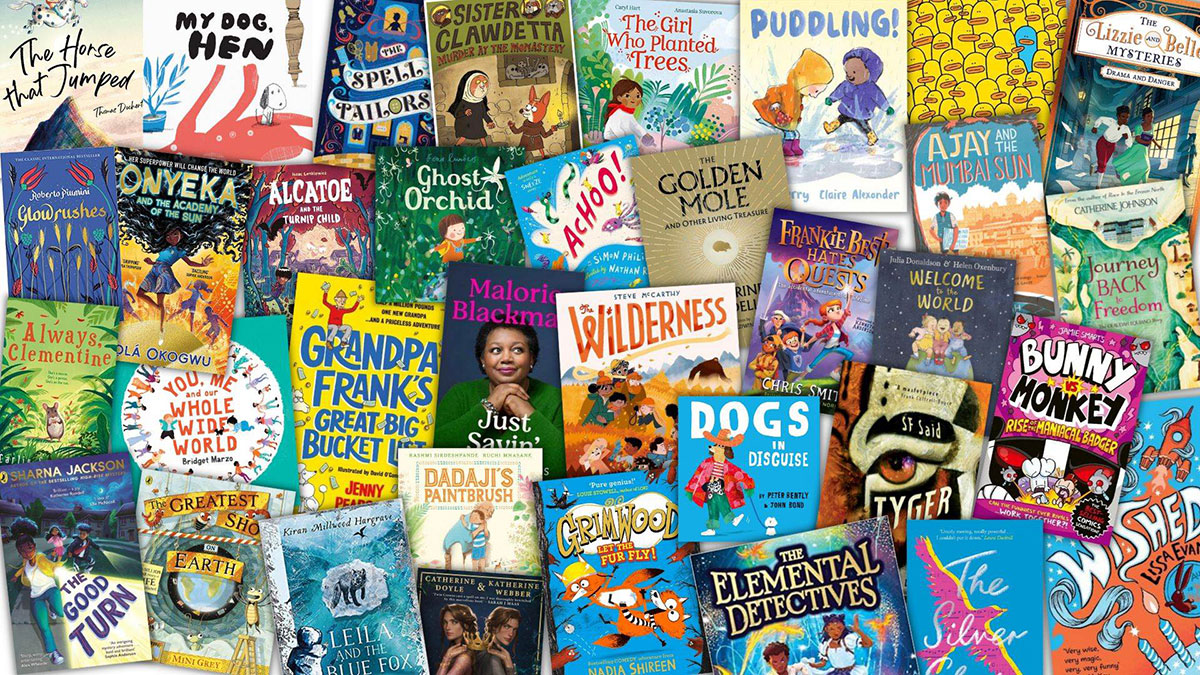
Stellen Sie sich das vor: Sie erschaffen eine Welt, in der jeder Buchstabe ein Baustein für das Abenteuer eines jungen Geistes ist. Es geht nicht nur um die Geschichte. Oh nein. Die besten Schriftarten für Kinderbücher?
Sie sind Schlüsselspieler auf der Bühne der Fantasie und führen kleine Augen durch verzauberte Wälder und Märchenländer, ohne zu stolpern.
In unserer Welt des Designs verwandeln sich diese Kringel und Linien in mächtige Werkzeuge, die das Zusammentreffen eines Kindes mit Worten formen.
Sie müssen lesbar sein, sicher, aber auch einladend – Freude und Verständnis im Tanz des Lesenlernens wecken.
Am Ende dieses Artikels werden Sie das Warum, das Was und das Wie verstehen, um die perfekte Schriftart für Ihre Geschichte auszuwählen.
Wir sprechen über kinderfreundliche Schriftarten, Informationen zu dyslexiefreundlichen Optionen und darüber, was Typografie nicht nur lesbar, sondern in den Augen unserer ehrlichsten Kritiker – den Kindern – entzückend macht.
Tauchen Sie mit uns ein, während wir den Kurs durch den Spielplatz der Schrifttypen festlegen und die Wunder der Harmonie von Illustration und Text eine verspielte Schriftart nach der anderen aufdecken.
Die besten Schriftarten für Kinderbücher
SchriftartLesbarkeitWärmeAltersgerechtigkeitEinzigartigkeit
Century SchoolbookAusgezeichnetMittelFür alle Altersgruppen geeignetKlassisch
AlegreyaSehr gutHochAm besten für ältere Kinder geeignetMarkant
Plantin InfantSehr gutMittelAm besten für junge Leser geeignetSanft
Bembo InfantSehr gutHochAm besten für junge Leser geeignetTraditionell
Sassoon PrimaryAusgezeichnetHochAm besten für junge Leser geeignetFür Bildung zugeschnitten
AndikaGutMittelFür alle Altersgruppen geeignetInformell
OpenDyslexicGutNiedrigFür alle Altersgruppen geeignetFür Dyslexie entworfen
QuicksandGutMittelFür alle Altersgruppen geeignetModern
Comic SansGutHochAm besten für junge Leser geeignetInformell
ChalkboardGutMittelAm besten für junge Leser geeignetLässig
KG Neatly Printed FontSehr gutMittelAm besten für junge Leser geeignetHandschriftlicher Stil
LatoSehr gutNiedrigFür alle Altersgruppen geeignetSchlicht
HelveticaSehr gutNiedrigFür ältere Kinder geeignetAllgegenwärtig
Gill SansGutNiedrigFür ältere Kinder geeignetKlassisch
GeorgiaSehr gutMittelFür alle Altersgruppen geeignetAuf Bildschirmen lesbar
Garamond ProSehr gutHochFür ältere Kinder geeignetElegant
CrimsonSehr gutHochFür ältere Kinder geeignetLiterarisch
FuturaGutNiedrigFür ältere Kinder geeignetGeometrisch
LillyGutHochAm besten für junge Leser geeignetVerspielt
Short StackGutHochAm besten für junge Leser geeignetKlobig und spaßig
Top Serifenschriften
Myriad Pro
In Ordnung, beginnen wir mit Myriad Pro. Es ist wie dieser Freund, mit dem man leicht auskommen kann – unkompliziert und freundlich. Diese Schriftart ist aufgrund ihrer Lesbarkeit eine hervorragende Wahl für längere Geschichten.
Georgia
Als nächstes, Georgia. Es ist wie der gemütliche Pullover unter den Schriftarten – bequem und vertraut. Seine leicht gerundeten Buchstaben sind perfekt für junge Leser und machen jedes Wort zu einer warmen Umarmung.
Garamond Pro
Garamond Pro führt uns mit einer klassischen Note zurück in die Vergangenheit. Es ist wie der weise Großelternteil unter den Schriftarten – voller Geschichten und Weisheit. Ideal für Märchen oder historische Geschichten.
Baskerville
Baskerville? Das ist die würdevolle Schriftart. Denken Sie daran als den Professor unter den Schriftarten – intelligent und respektiert. Sie verleiht jedem Buch einen Hauch von Eleganz.
Plantin Infants
Und dann Plantin Infants – speziell für unsere jüngsten Leser entwickelt. Es ist wie der sanfte Führer, der ein Kind auf seiner Lesereise an der Hand hält.
Alegreya
Alegreya kommt mit ein wenig Flair daher. Es ist wie die abenteuerlustige Tante, voller Überraschungen. Großartig für Geschichten, die ein wenig Drama und Aufregung benötigen.
Century Schoolbook
Century Schoolbook ist der Mentor – zuverlässig und vertrauenswürdig. Diese Schriftart ist seit langem dabei, Kindern das Lesen beizubringen. Eine solide Wahl für Bildungsbücher.
Crimson
Crimson schließt unsere Liste mit seiner zurückhaltenden Eleganz ab. Es ist die ruhige Schriftart in der Ecke, aber wenn man sie kennenlernt, steckt voller Tiefe und Charakter.
Top Schriftarten ohne Serifen
Andika (kostenlose Google-Schriftart)
Beim Wechsel zu Schriftarten ohne Serifen tritt Andika zuerst auf. Es ist modern und zugänglich, ähnlich wie der coole technikaffine Cousin. Außerdem ist es kostenlos!
Helvetica
Dann gibt es Helvetica, den Alleskönner. Diese Schriftart ist überall und aus gutem Grund. Es ist wie der zuverlässige Freund, der immer für Sie da ist.
Gill Sans
Gill Sans ist der Künstlerische. Es hat Stil, ohne es zu übertreiben. Perfekt für Bücher, die eine kreative Note brauchen, ohne übertrieben zu wirken.